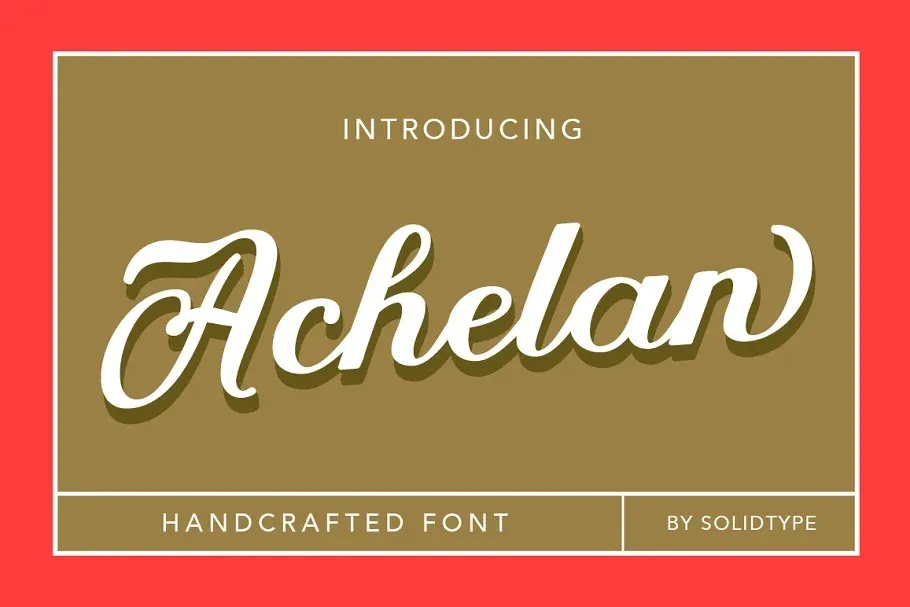
Achelan Font – Fonte Grátis
Achelan Font
A Achelan Font é uma elegante tipografia moderna do estilo script que oferece linhas limpas e suaves, desenvolvida pela Solidtype. Este tipo de letra traz ao seu design um toque sofisticado, ideal para os ambientes de moda e comunicação visual atuais. Josephine é parte desta paleta, com seus vários conjuntos alternativos estilísticos que permitem diferentes interpretações do mesmo texto. A Achelan Font se destaca por sua versatilidade, sendo perfeitamente adaptável a uma variedade de finalidades, desde materiais publicitários e roupas personalizadas até logotipos, identificações visuais e selos de notícias. Com suporte internacional para mais de 80% dos idiomas ocidentais, esta fonte é uma ótima escolha para aqueles que desejam expandir seus designs em línguas estrangeiras.